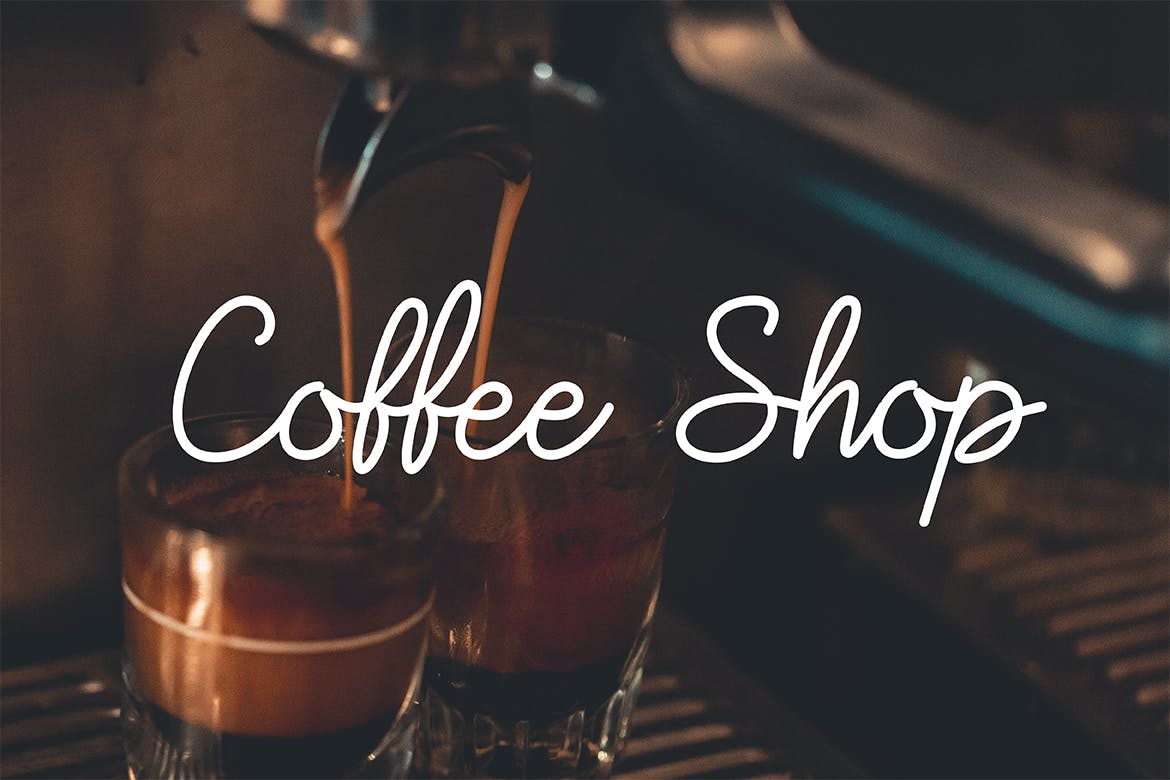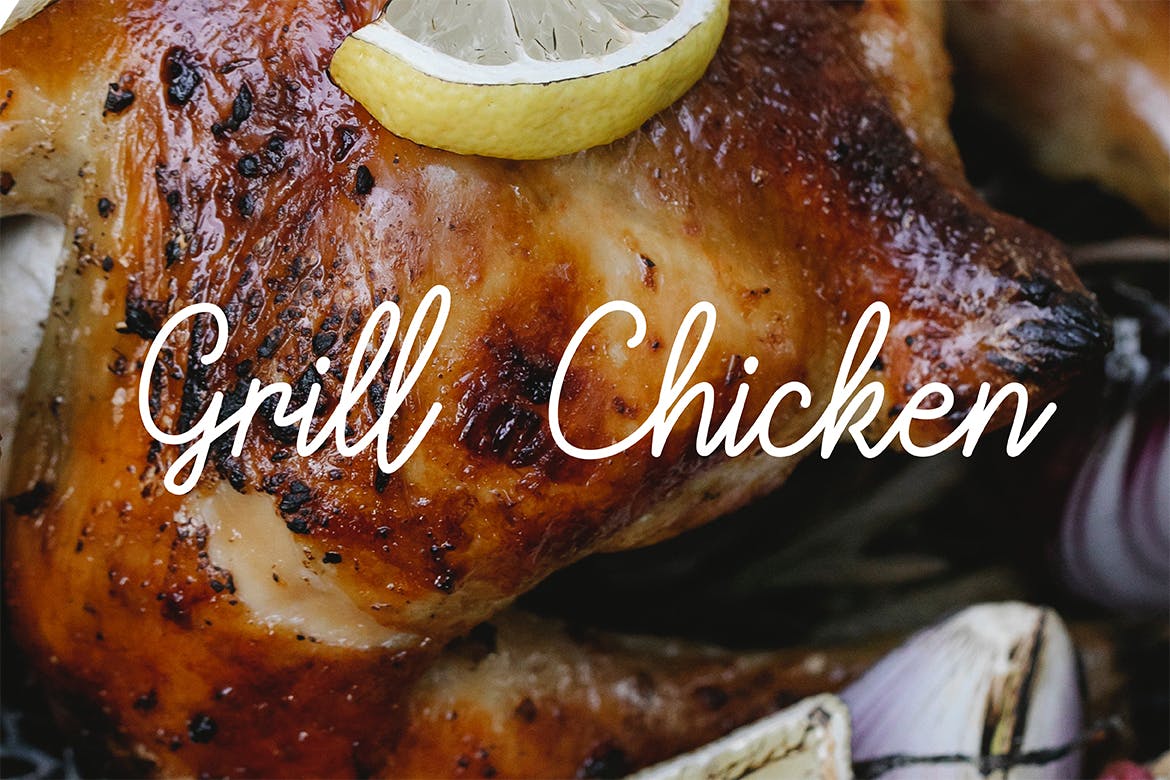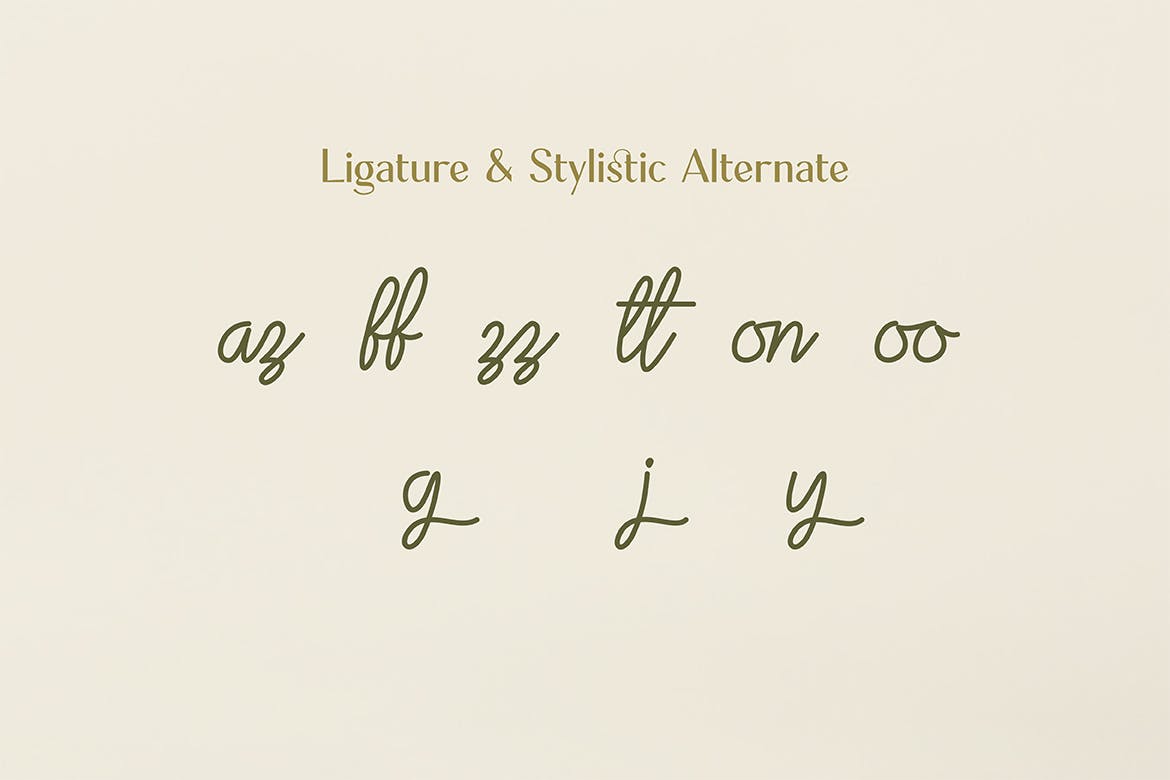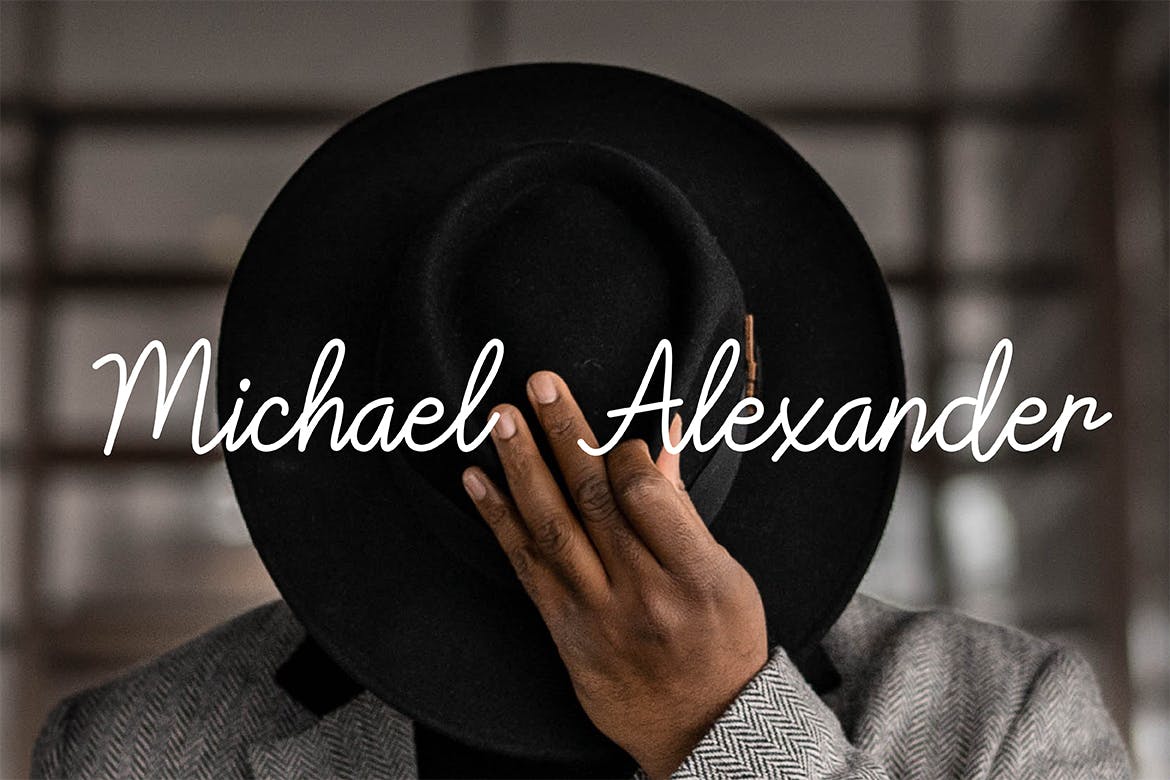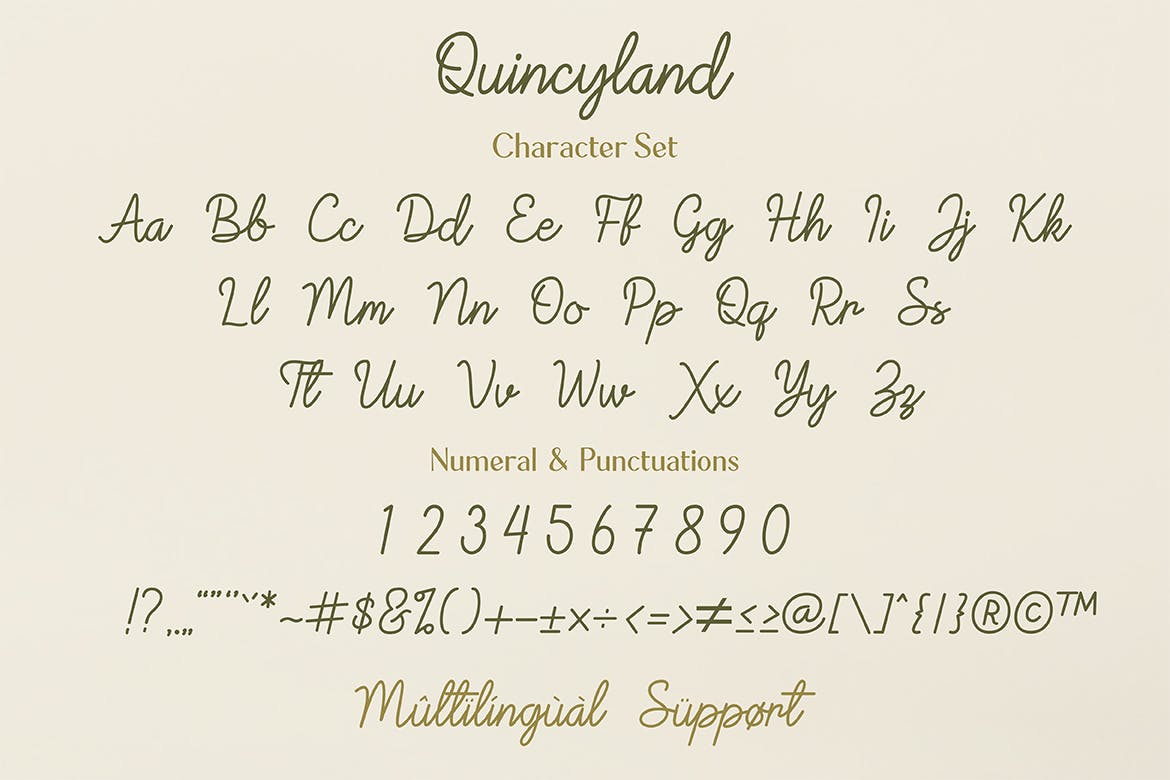
دانلود فونت اسکریپت مدرن Quincyland
Modern Script Font
فونت اسکریپت مدرن Quincyland برای طراحی‌های خلاقانه شما مناسب است.
فونت اسکریپت مدرن Quincyland یک انتخاب عالی برای طراحان و هنرمندان است که به دنبال افزودن زیبایی و اصالت به پروژه‌های خود هستند.
• حروف بزرگ
• حروف کوچک
• اعداد و نشانه‌گذاری